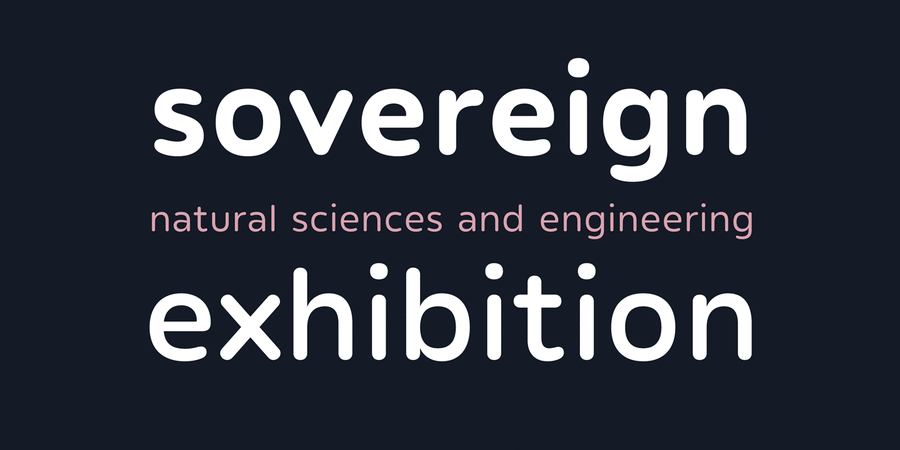
Apoka Pro – це заокруглений гротеск з 6 накресленнями, розширена версія шрифту Apoka, випущеного раніше. Сімейство Apoka Pro підтримує як латинку так і кирилицю. Знаки мають помірний контраст, а краї м'яко заокруглені. Особливість шрифту полягає в стриманій простоті та увазі до деталей. Apoka Pro найбільше підходить для брендингу, вивісок, упаковки, інтерфейсів і веб-дизайну, має альтернативні гліфи і функції OpenType, такі як дроби, верхні та нижні індекси. Шрифт розробила Марія Пігулевська у 2017 році. Apoka Pro™ є торговою маркою компанії The Northern Block.
Асоціації з сімейством шрифтів Apoka ProОсобистість і характер гарнітури:
делікатний, чистий, легкий, прохолодний, свіжий, модний, тонкий, сучасний, лаконічний, якісний, невагомий, прозорий, інтимний, крихкий, ніжний, повітряний, дротяний, неоновий, худий, спокійний, мирний, ясний, рівний, смачний, зрозумілий, М'який, приємний, комфортний, симпатичний, зручний, домашній, милий, добрий, привітний, дитячий, щедрий, пишний, доброзичливий, затишний, гладенький, пластмасовий, Простий, сімейний, рясний, насичений, наївний
краса, туалетна вода, дієта, АСМР, ранок, світанок, дизайн, лосьйон, шампунь, перукарня, латте, інтер'єр, Інстаграм, йога, вода, небо, ліки, здоров'я, мафін, смузі, одяг, взуття, спальня, дім, селфі, їжа, дитяча книжка, молоко, дитяче харчування, розфарбування, торгівля, сир, кондитерська, солодощі, випічка, булочна, кафе, чай, родина, кава, іграшка, шоу, телебачення, підгузок, малюк, булочки, булочка, десерт, гра, м'яка іграшка, соус, сметана, кетчуп, чіпси, подушка Гарнітура має ознаки стилів: